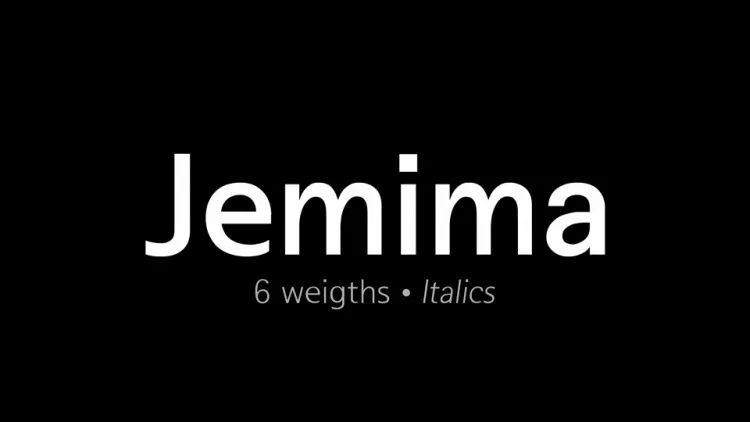
Jemima Font Family
A Jemima Font Family é uma sans serif que desperta forte interesse por sua identidade única, inspirada no Rotis Sans Serif. Suas formas únicas e linhas contrastantes criam um design memorável com um toque elegante e fluido. O conjunto vem equipado com seis pesos diferentes, incluindo itálico para um contraste atraente. Esta família de fontes oferece uma experiência visual agradável, adequada tanto para aplicações formais quanto descomplicadas. Além disso, a Jemima Font Family se destaca por suportar gregos e cirílicos, permitindo maior flexibilidade e inclusividade no design. Seja você um designer de interface do usuário ou uma marca que busca personalização em seu logotipo, este conjunto de fontes oferece o ideal para expressar sua identidade visual de maneira distintiva.